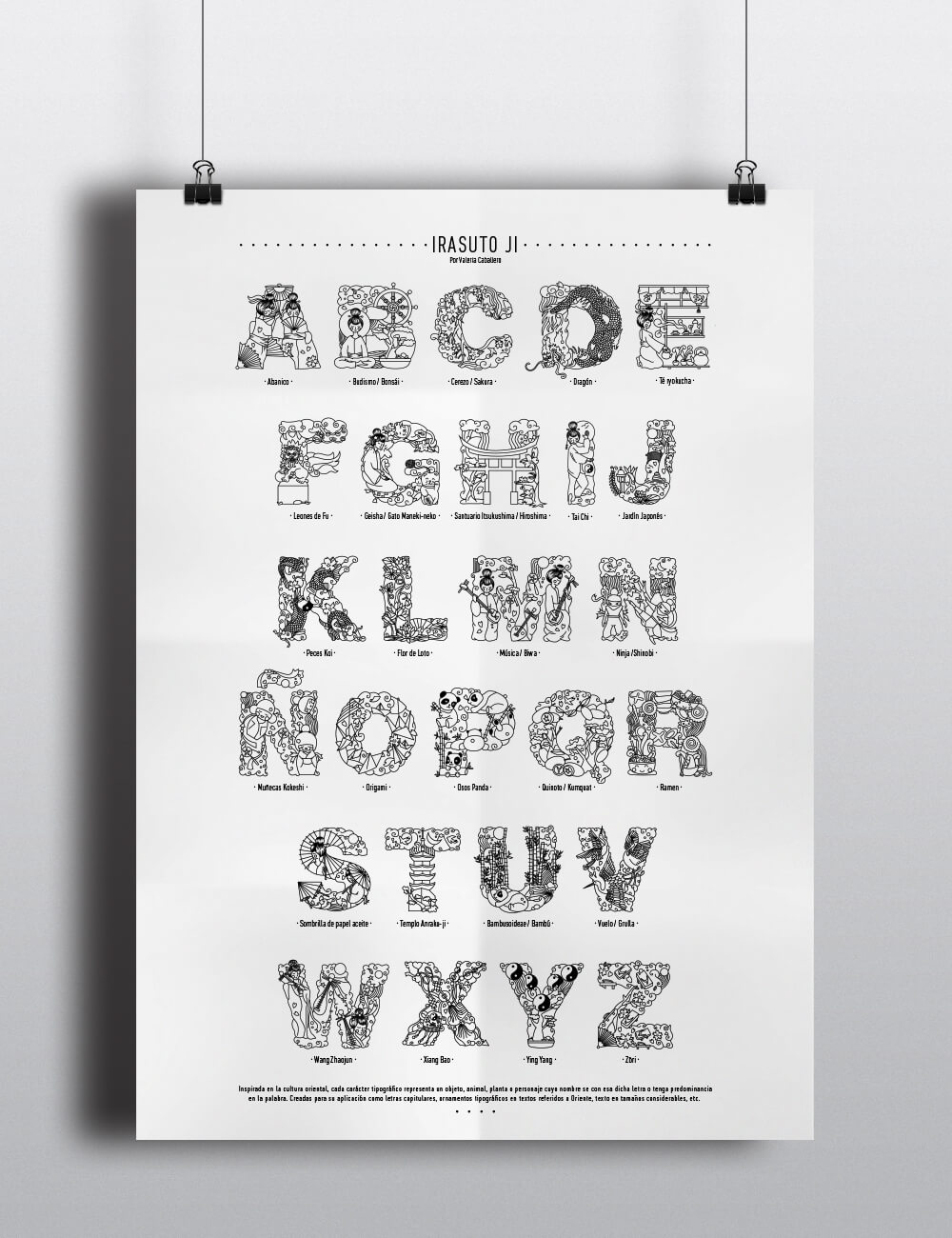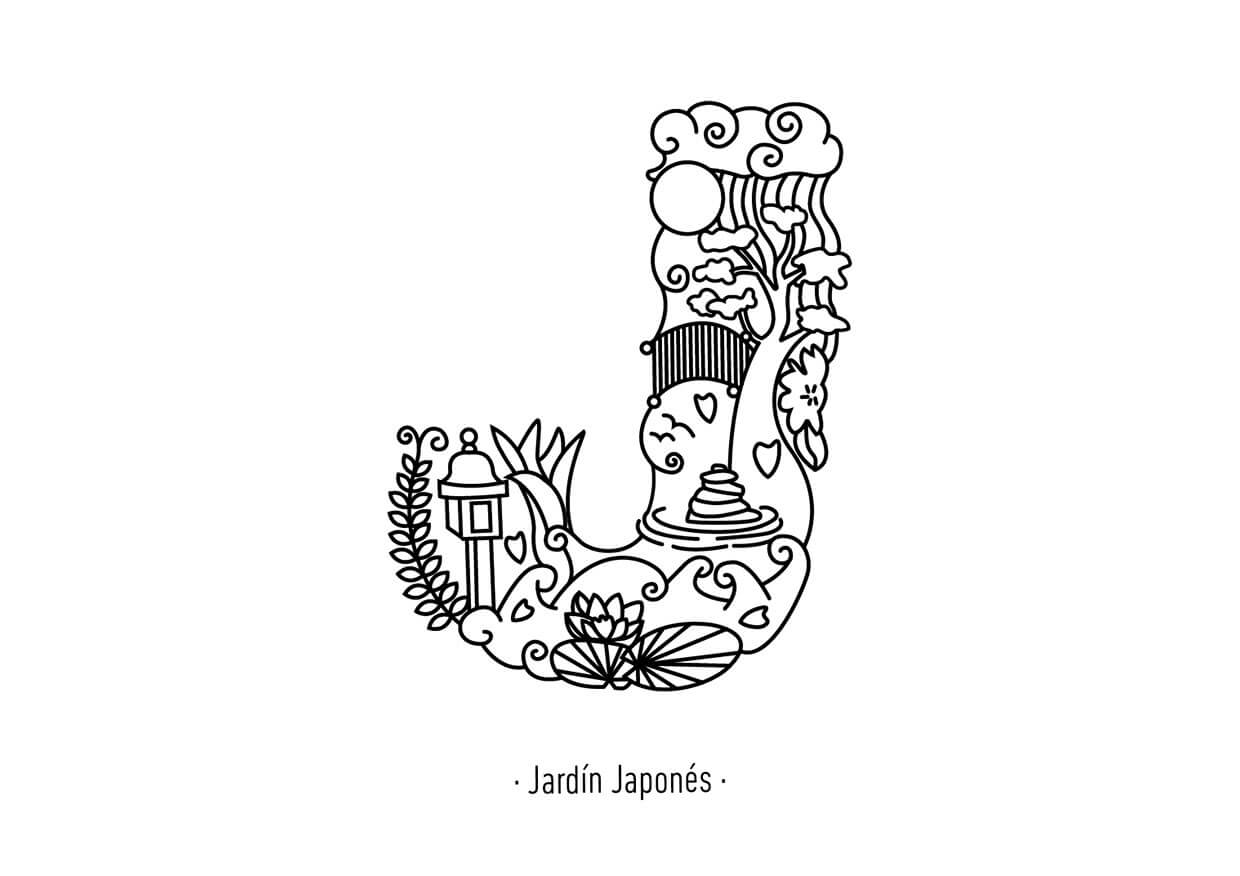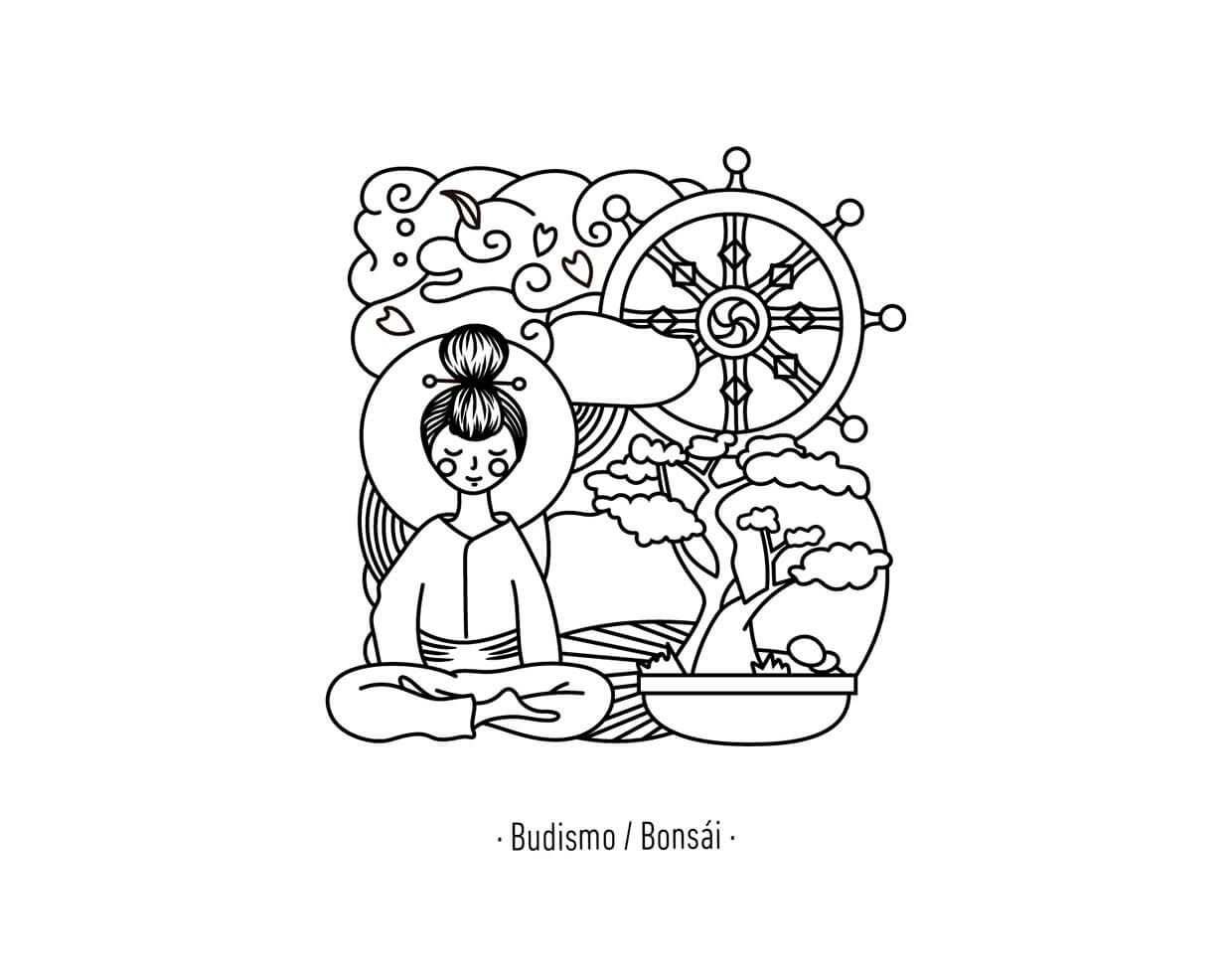
Hoy nos fijamos en el trabajo de la argentina Valeria Caballero. Irasuto Ji es una tipografía inspirada en la cultura oriental, cada carácter tipográfico representa un objeto, animal, planta o personaje cuya denominación se inicia con esa letra.
Creadas para su aplicación en letras mayúsculas, ornamentos tipográficos en textos referidos a Oriente, texto en tamaños considerables, etc…